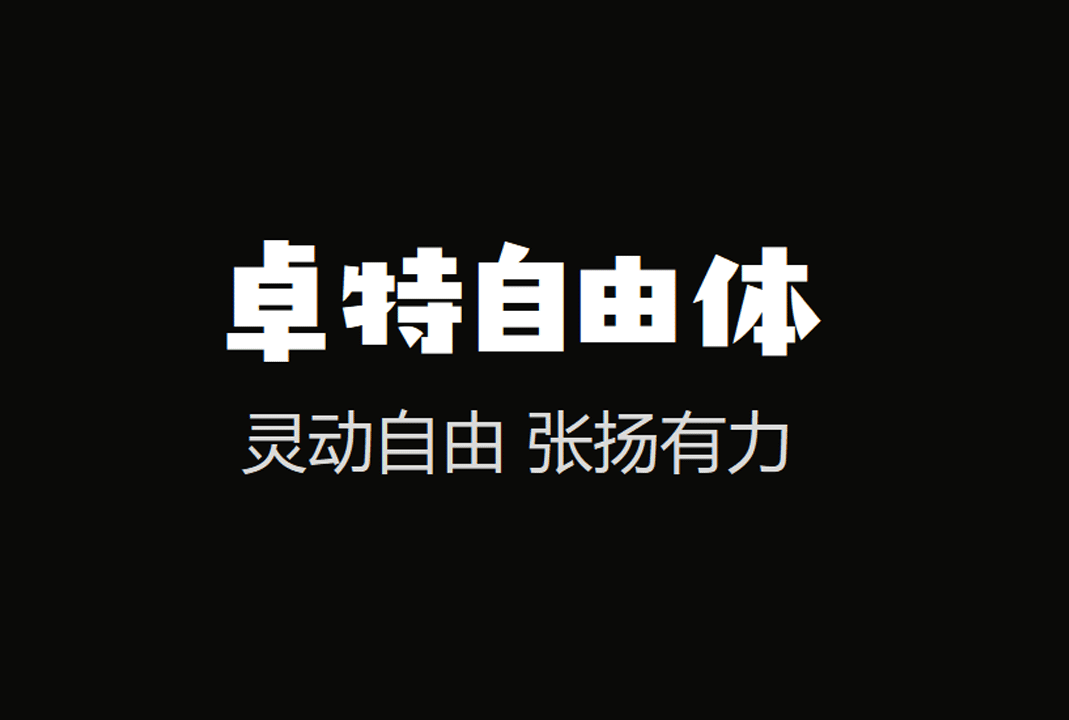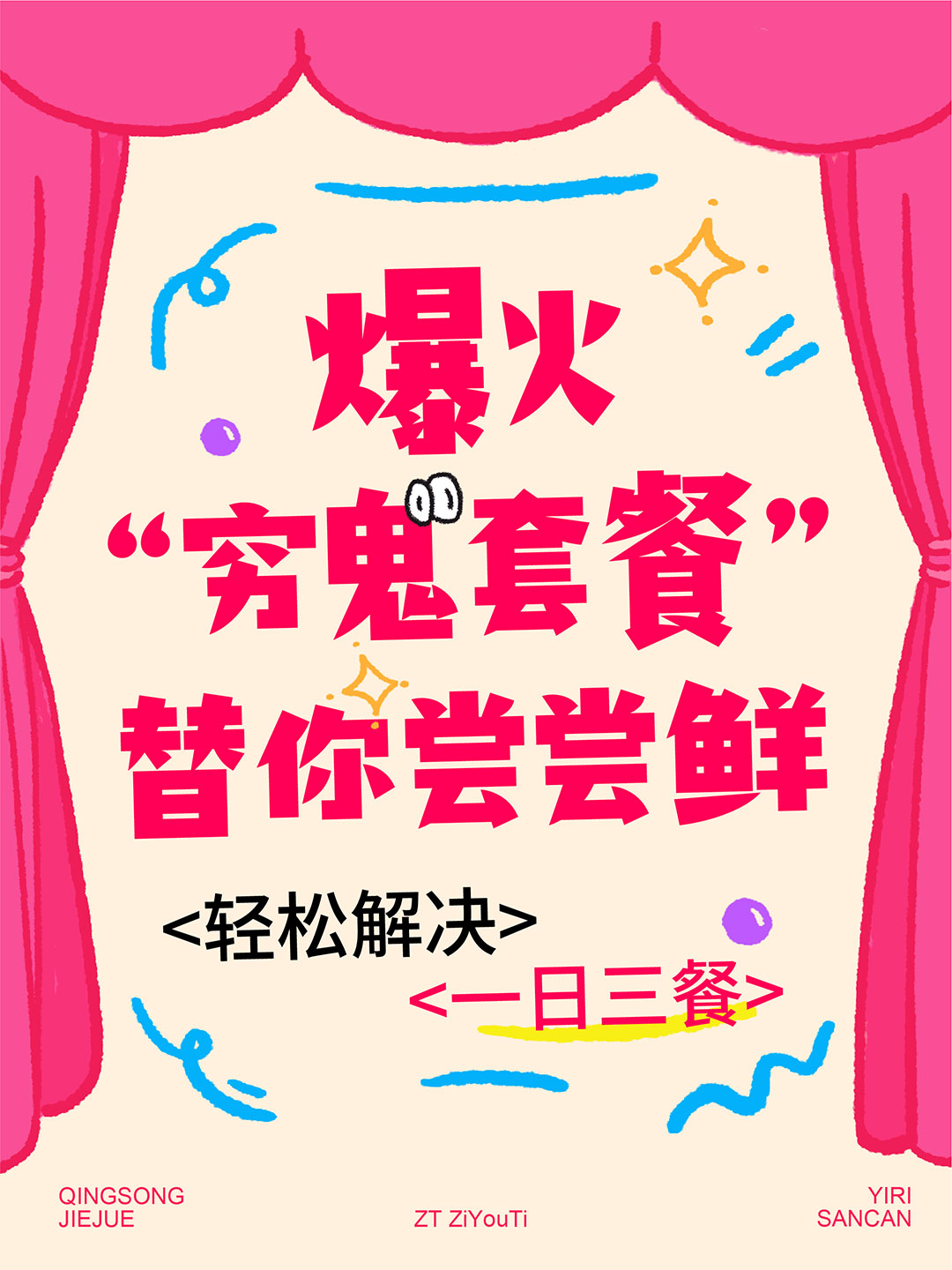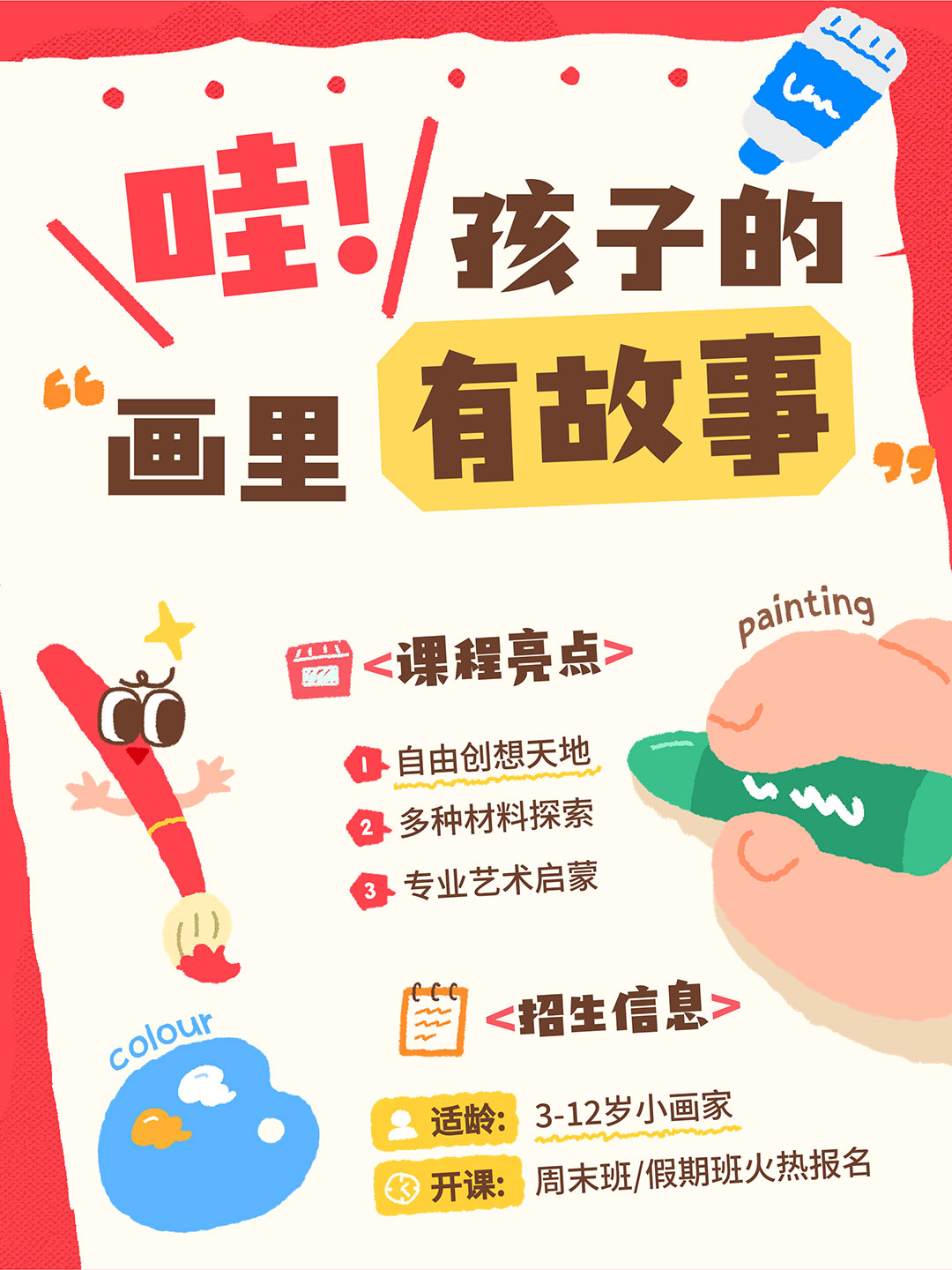
卓特自由体_免费商用中文字体下载
卓特自由体是由卓特视觉携手国内知名字体设计师刘兵克,为创意人群打造三款风格迥异的免费字体之一。
卓特自由体字形结构宽阔,大小错落,节奏感强烈。笔画粗实有力,几何感强,整体风格张扬惊艳,极具视觉冲击力,适合各类专业场景使用。包含 GB2312-80 标准中的 6763 个简体汉字及 420 个常用字符,共收录 7183 个字符,可满足日常办公、设计创作、品牌宣传等多元场景的字体使用需求。
字形案例展示: